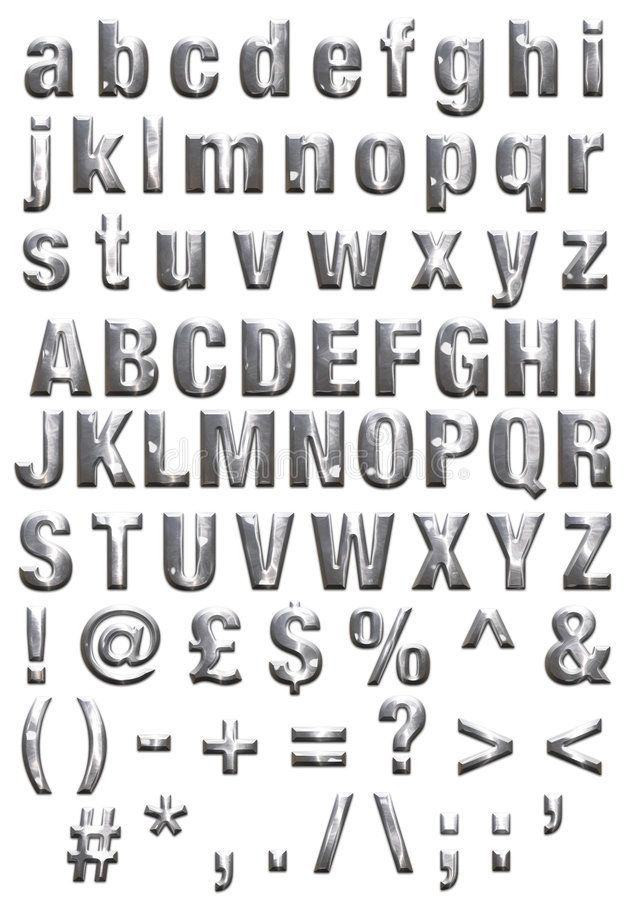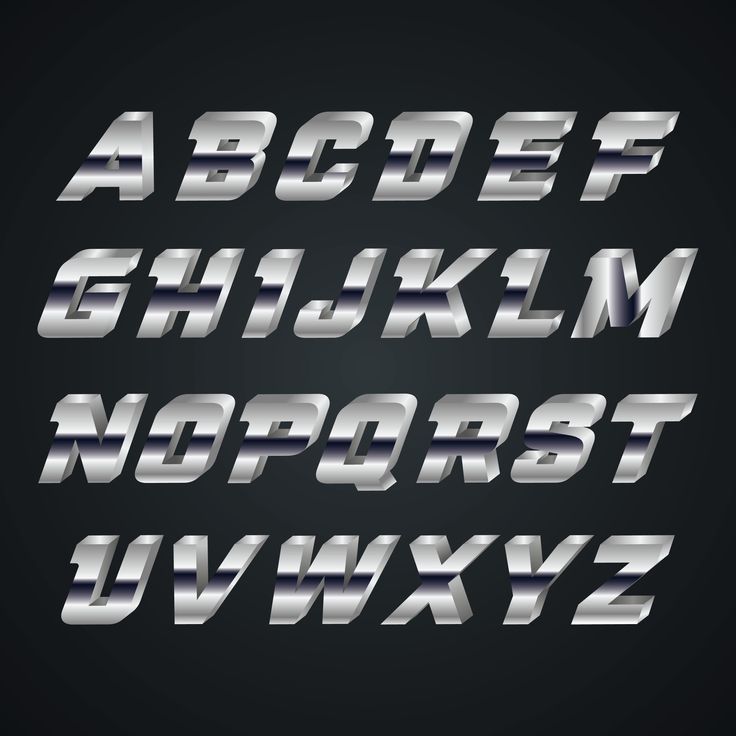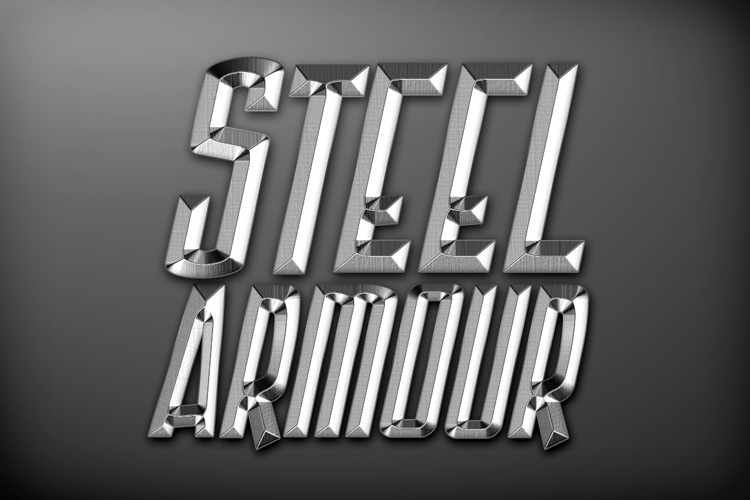
Шрифт металлические буквы русский. Лучшие бесплатные шрифты для дизайнеров. Информация о коллекции шрифтов
Шрифт меча
Шрифт Sword был разработан Гарри Касьяновым и состоит из четырех шрифтов в двух форматах: OpenType Font и TrueType Font. Эти два формата можно комбинировать: угловой меч, прямоугольный меч, угловой меч с тенью и меч с прямоугольной тенью.
Шрифт меча содержит 5 глифов для нижнего регистра, 4 глифа для верхнего регистра и 4 альтернативы для каждого числа вместе с набором символов от A до Z. Он также поддерживает несколько языков.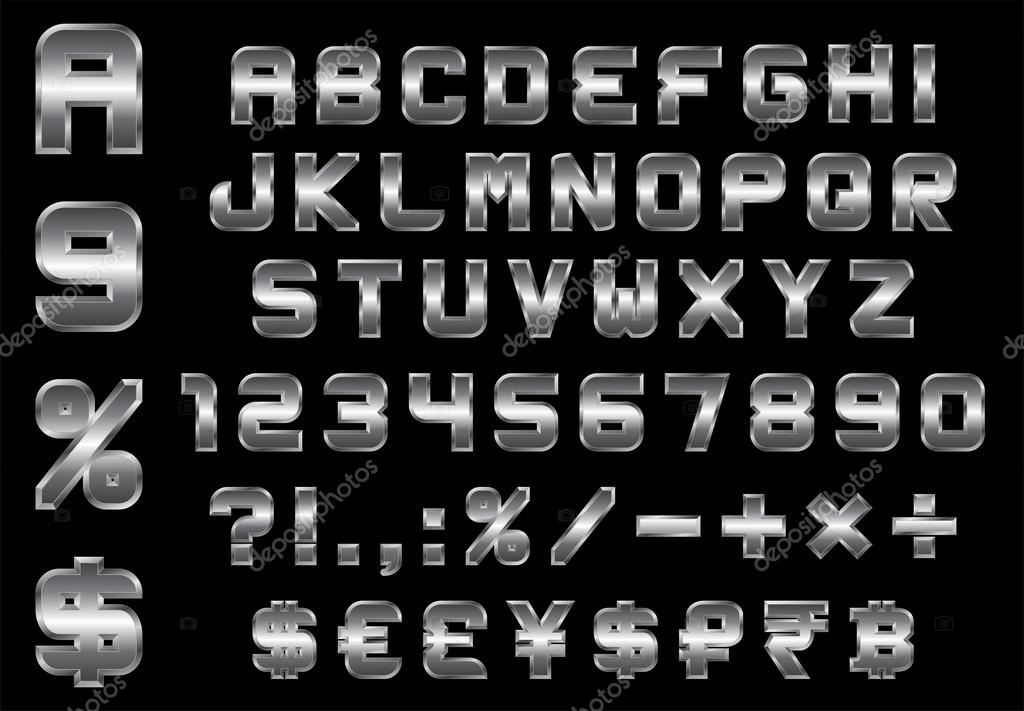